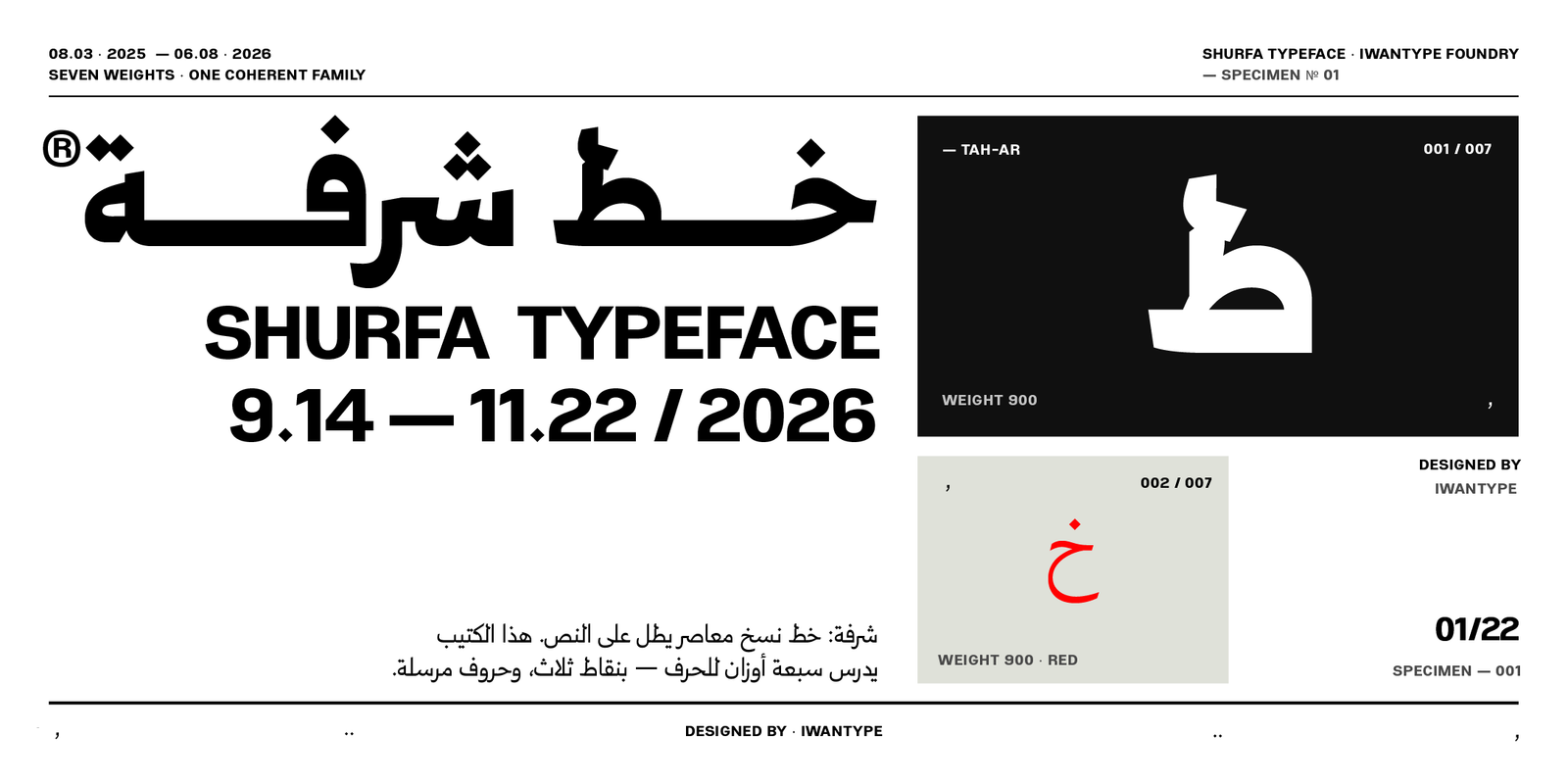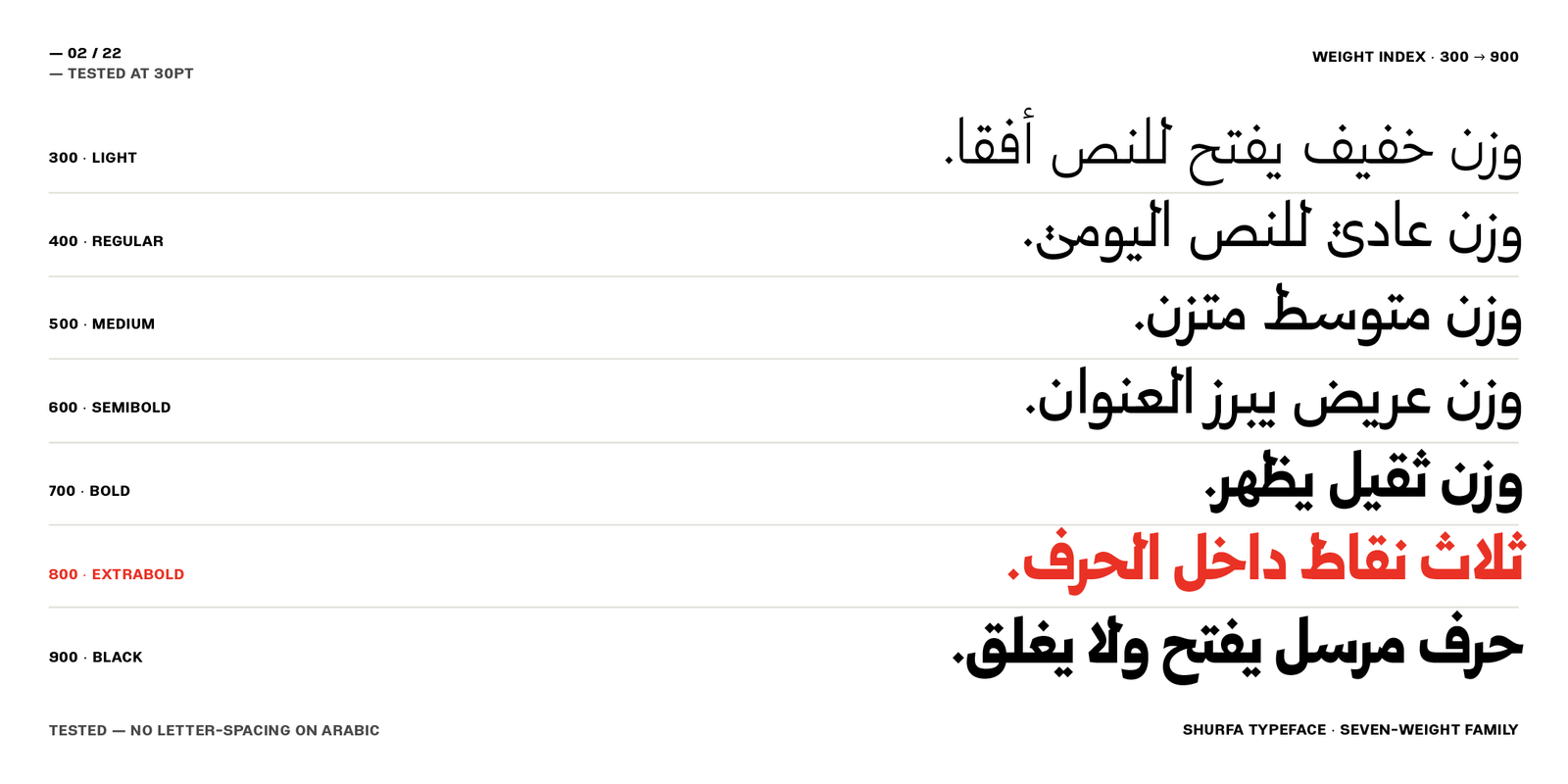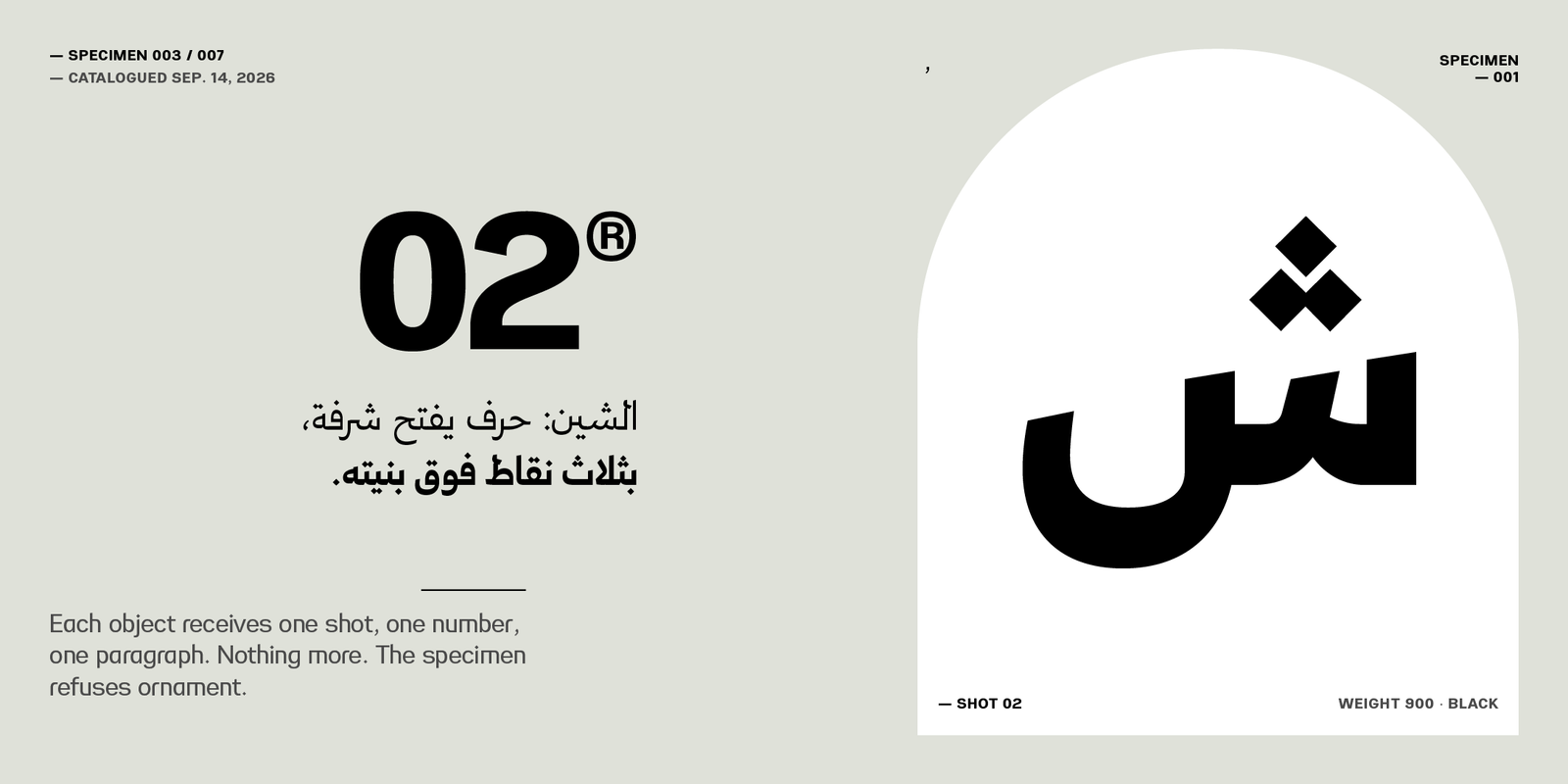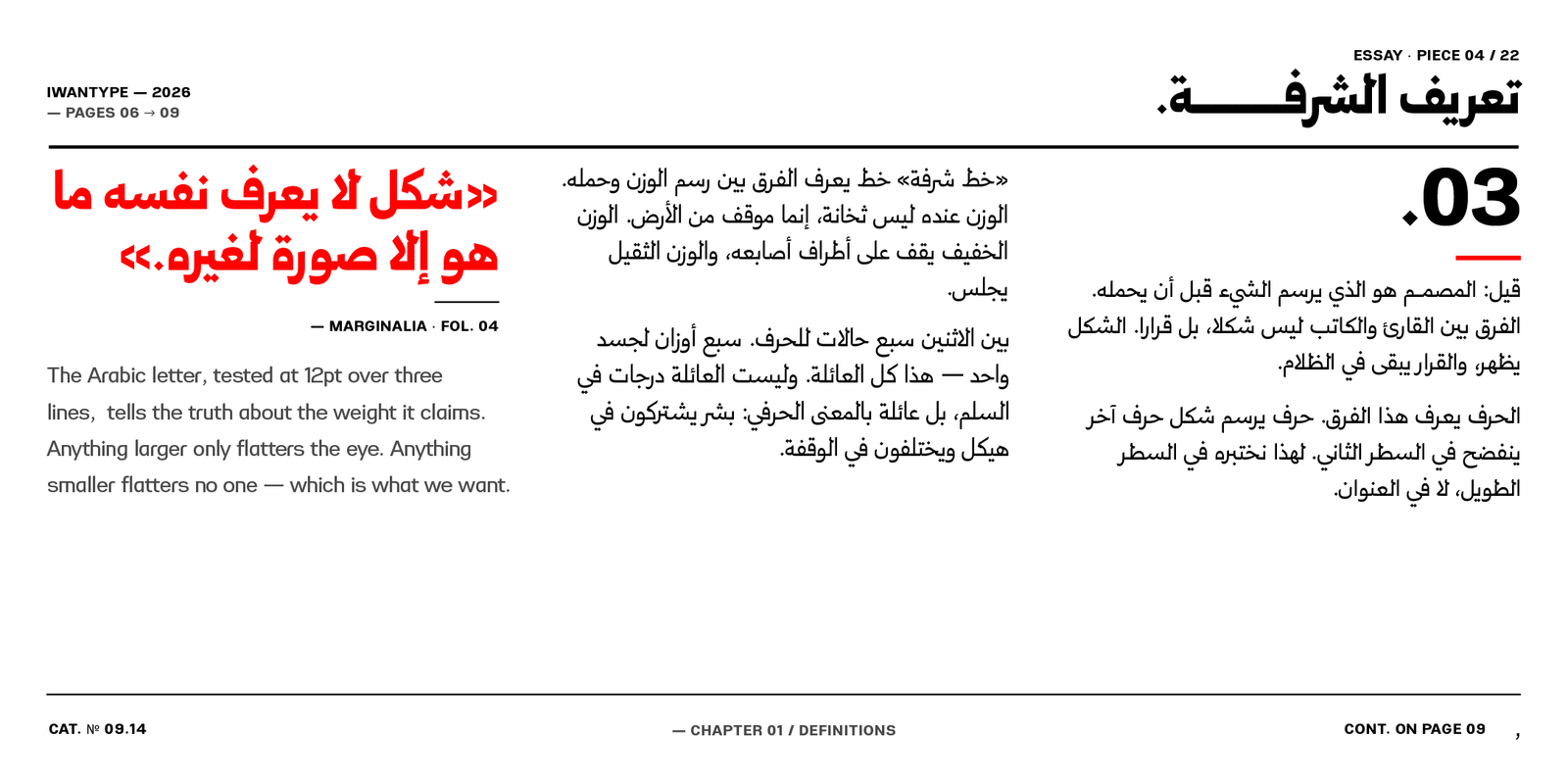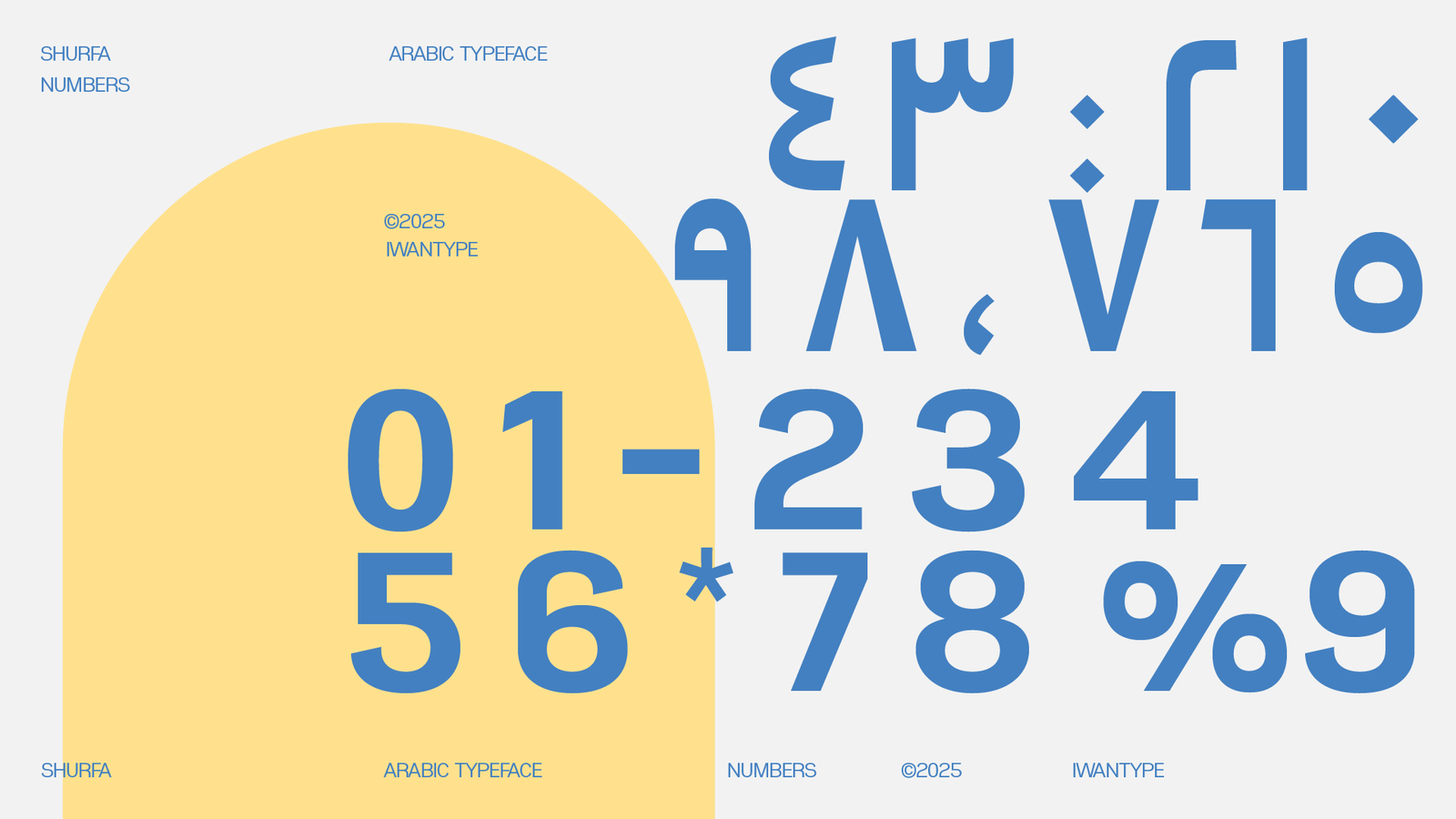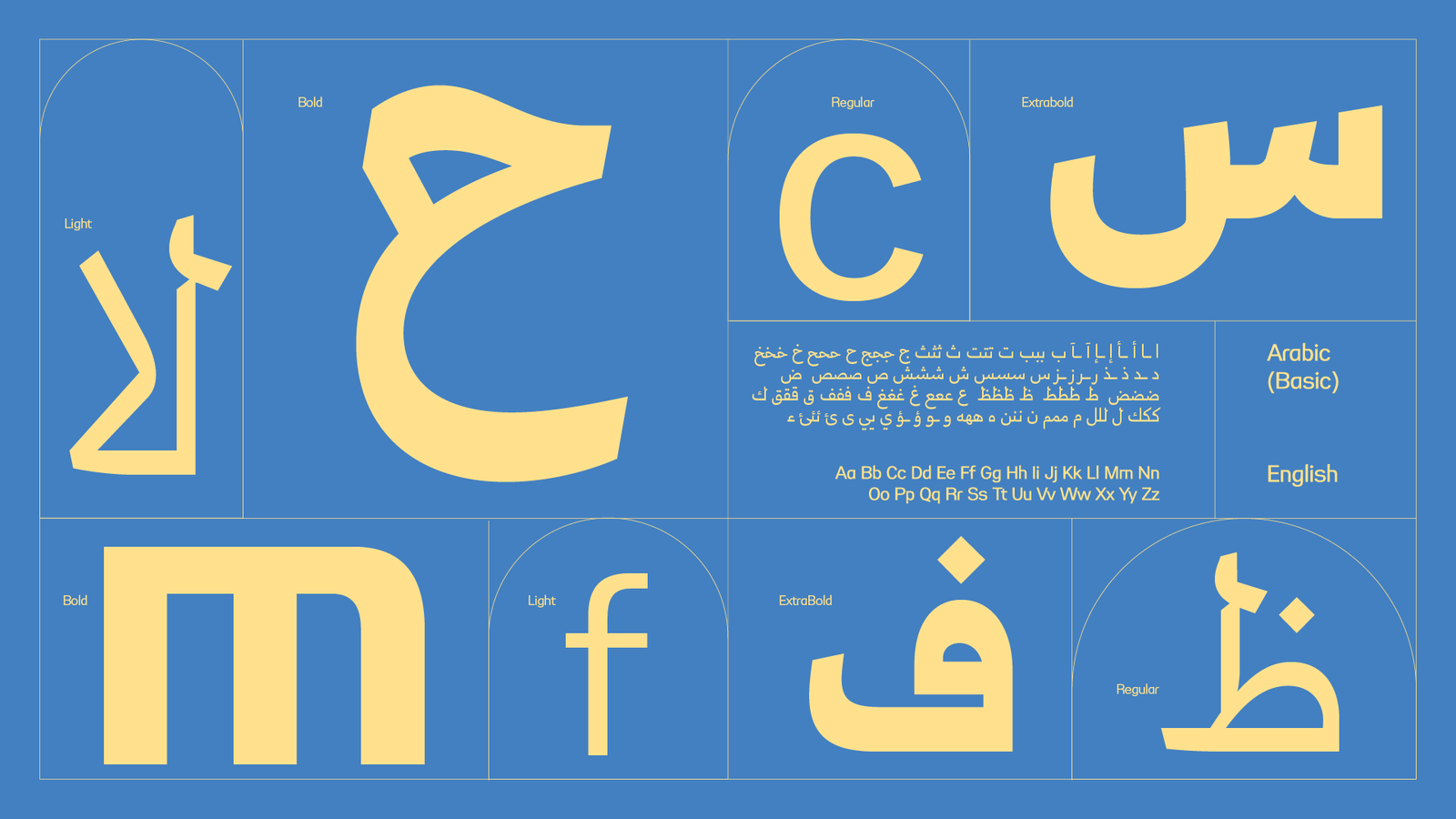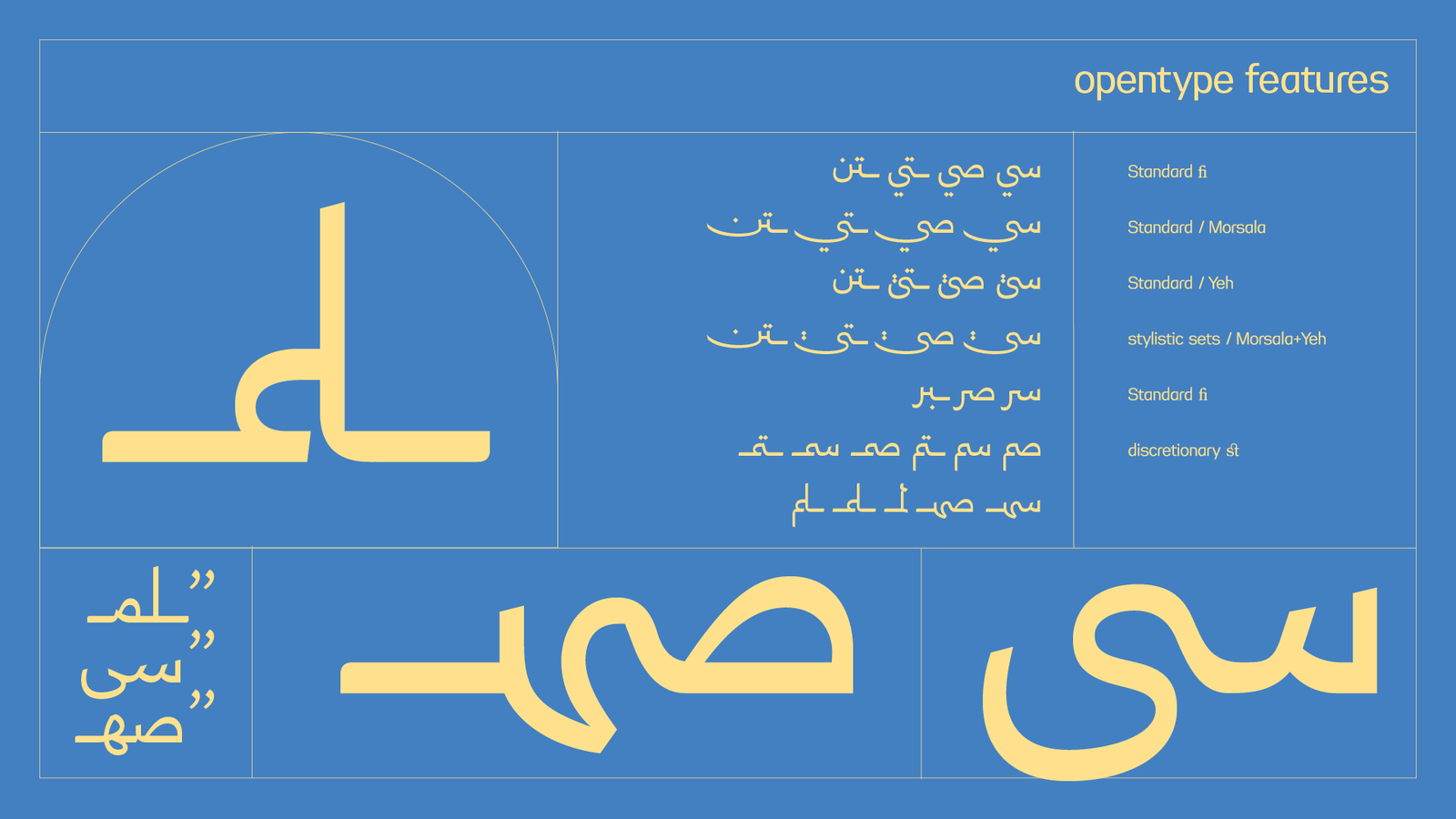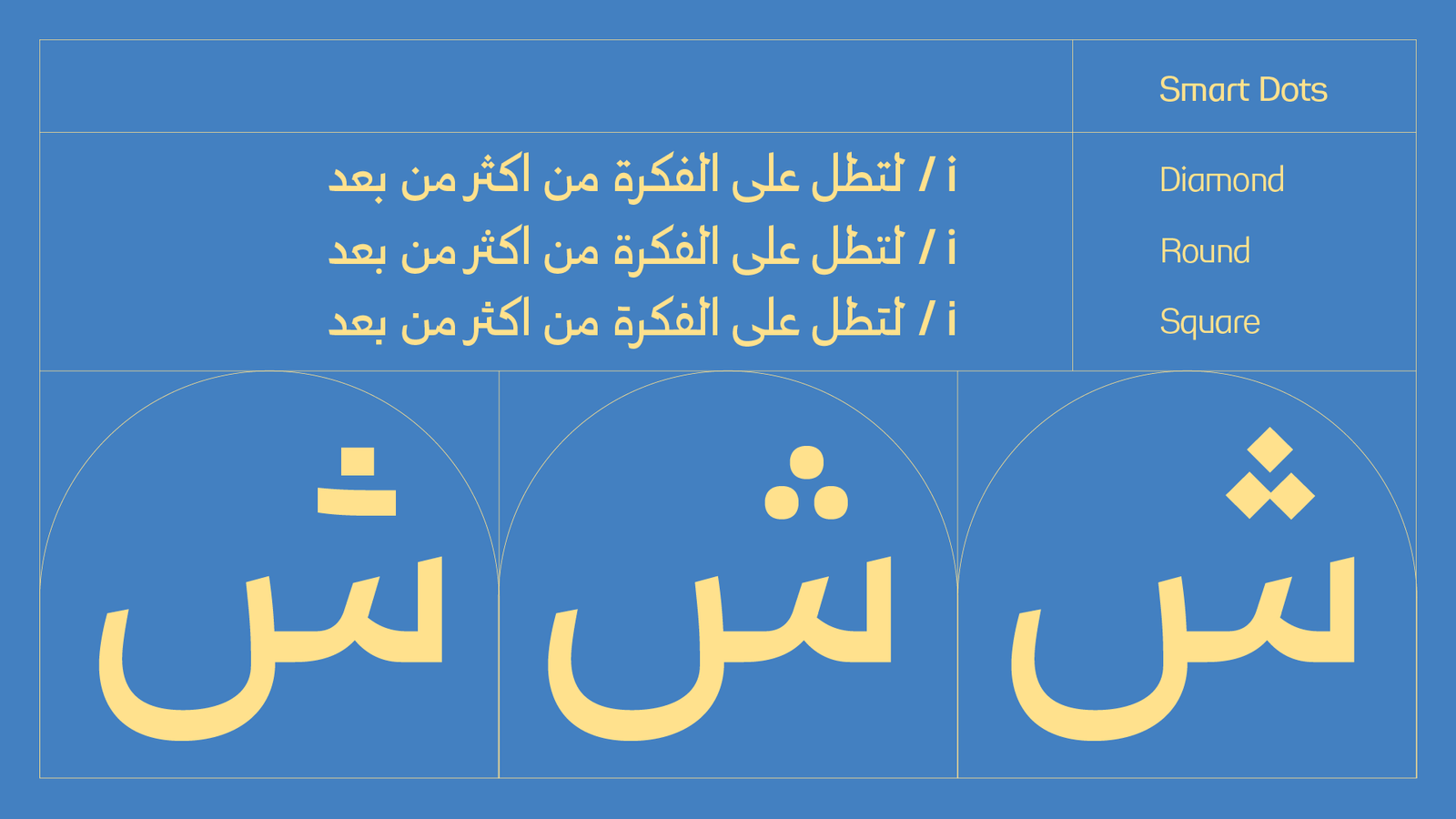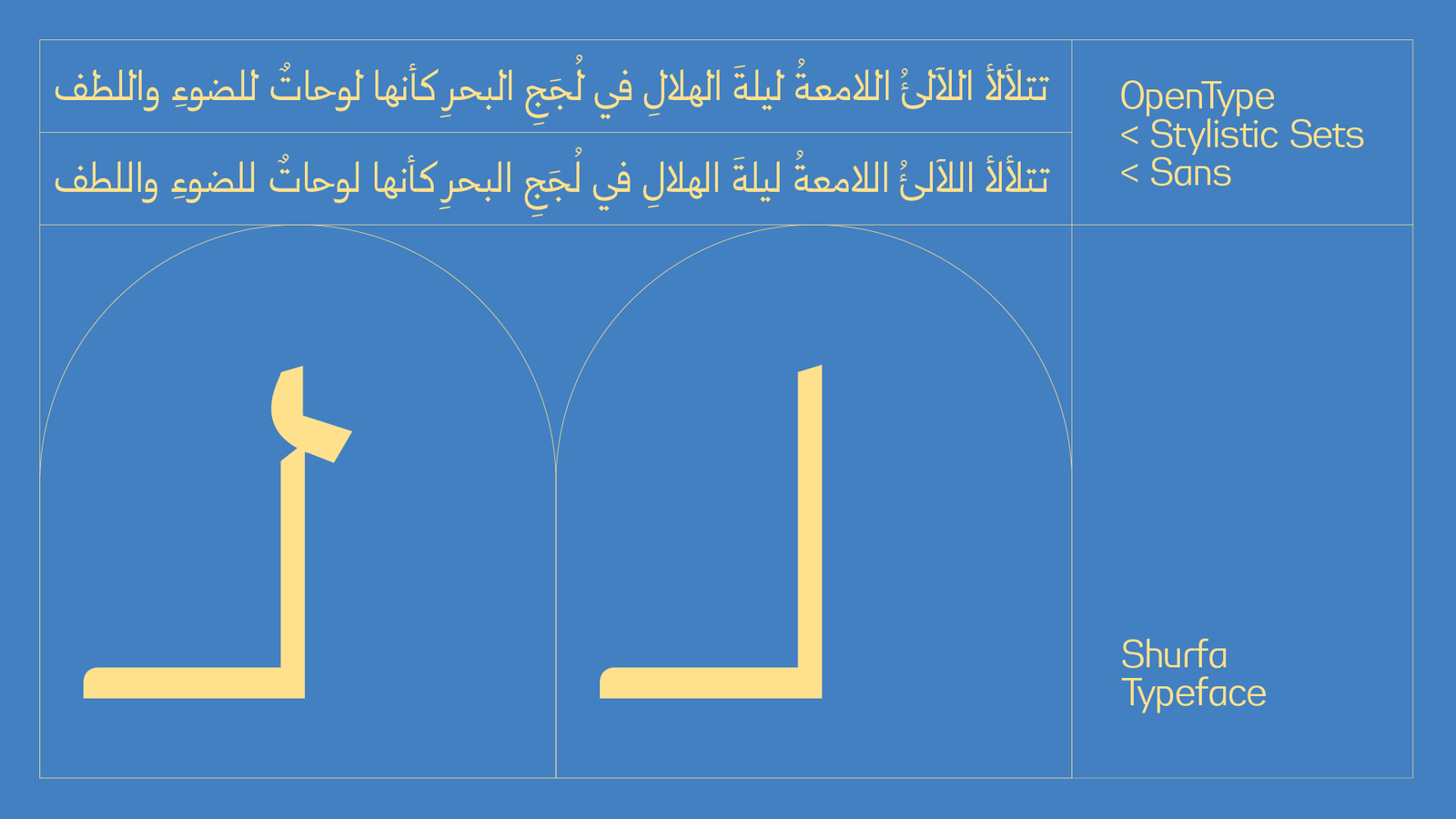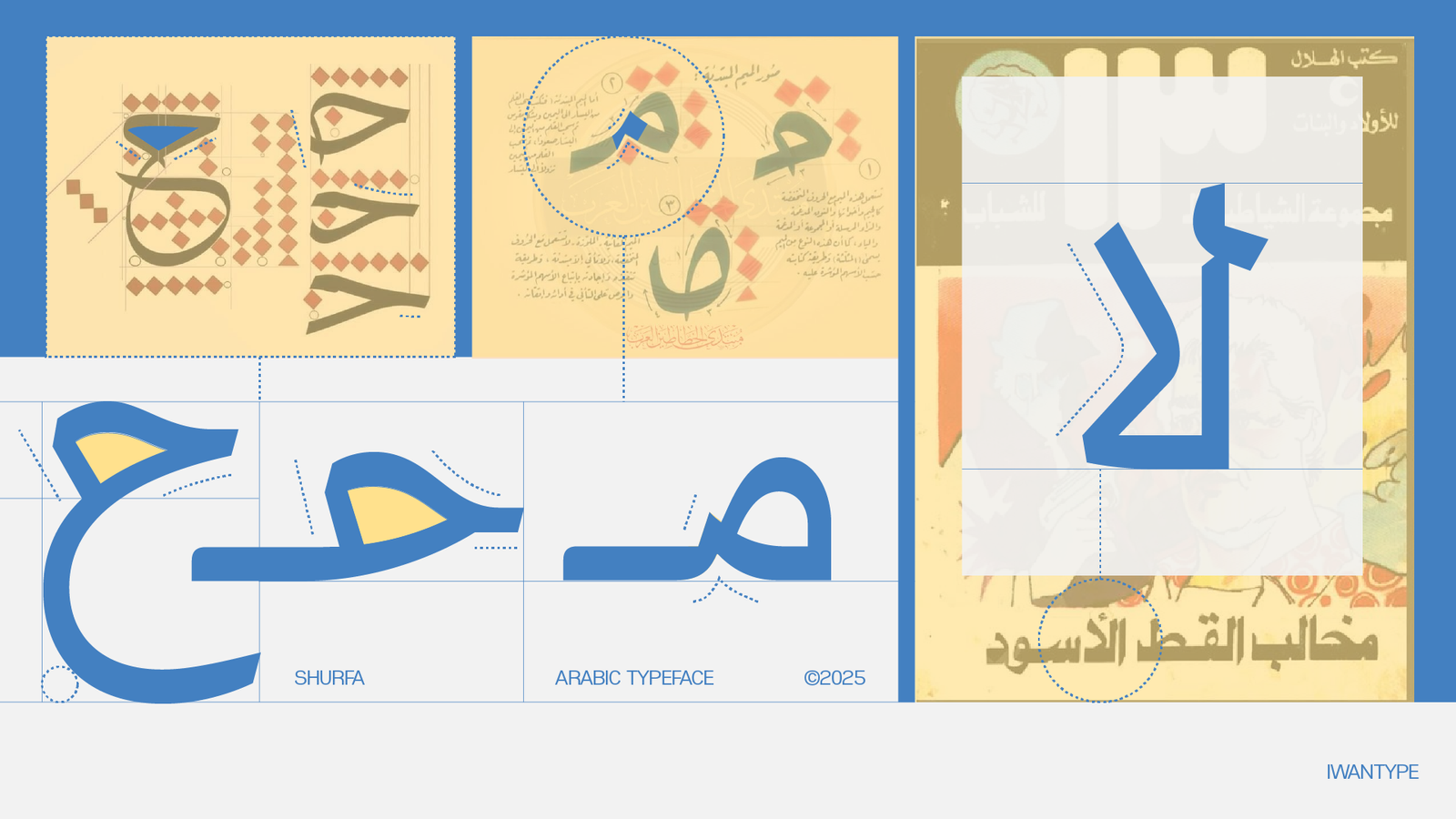
خط شرفة الطباعي – خط نسخ – Shurfa typeface
خط «شرفة» هو خط عربي طباعي مبني على أسلوب النسخ المسطري، ومستوحى من التفاصيل والأساليب البصرية لخط الثُلث.
يتكون الخط من سبعة أوزان مختلفة تتراوح من الخفيف إلى الأسود ، ومصمم للاستخدام في العناوين، والنصوص القصيرة والمتوسطة، ومختلف التطبيقات الطباعية والرقمية.
يتميز خط شرفة بتصميم واضح ومرتكز على السطر، ويعكس دمجًا بين خصائص النسخ المسطري وبنية الثُلث.
الخط مناسب لاستخدامات التصميم الجرافيكي، وتصميم الهويات البصرية، والعناوين الرئيسية في المنشورات المطبوعة والرقمية.
مميزات خط شرفة الطباعي:
مزايـا OpenType: يتضمن الخط العديد من مزايا OpenType التي تضفي عليه مرونة وتنوعًا في الاستخدام، مثل:
- الحروف المرسلة: لمسة تقليدية تضفي على النصوص جمالية خاصة.
- حرف ياء بنزول أقل: يقلل من نزول السطر، مما يعزز من انتظام النصوص.
- النقطات البديلة: توفر تنوعًا وجاذبية بصرية إضافية للنصوص.
- الحروف المركبة: تسهم في تحسين المظهر العام للنص وتزيد من سلاسته.
الأوزان: سبعة أوزان.
اللغات : العربية والإنجليزية